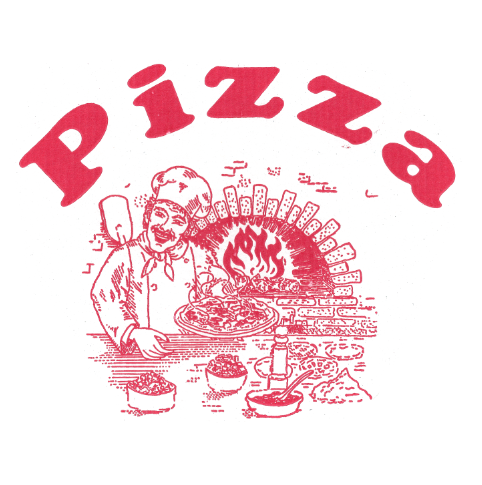
Suche Schrift von Pizza-Karton.
Ich suche folgende Schrift eines Pizza-Kartons.
Vielleicht kennt ja jemand diese…oder eine sehr ähnliche Schrift.
Sehr verbreitet sind auch Pizza-Kartons, bei der zusätzlich ein Grün zum Einsatz kommt. Mit Italien-Flaggen, Ofen ohne Koch und einem Pizza-Schriftzug, der grob einen Viertelkreis beschreibt, siehe https://www.google.com/search?q=pizzakarton&tbm=isch.
Bei diesem Karton ist der Schriftzug in der Arnold Böcklin angelegt (oder in der Arabia, das ist ein Klon, der mit CorelDRAW geliefert wird/wurde(?), sagt Wikipedia dazu).